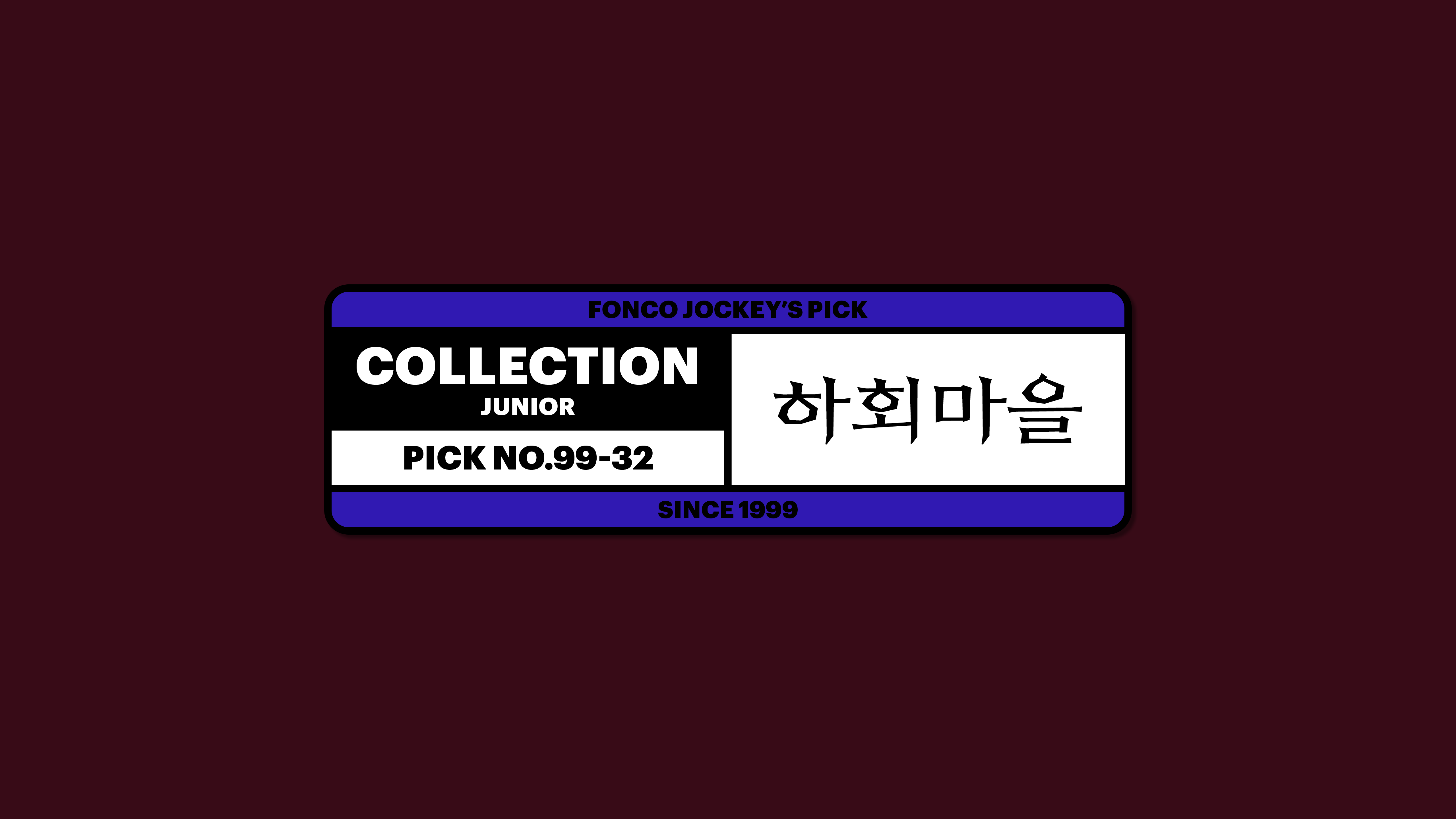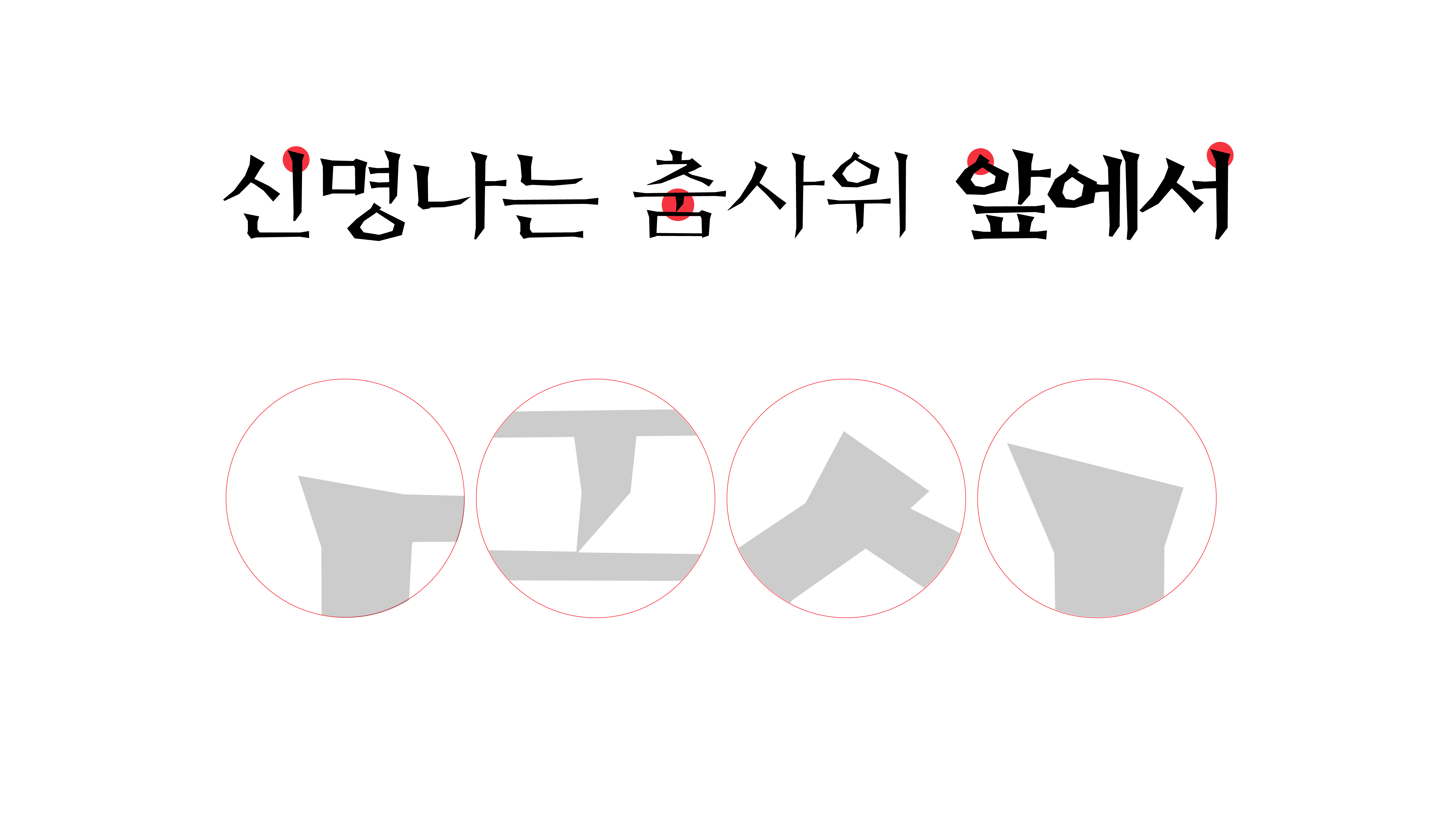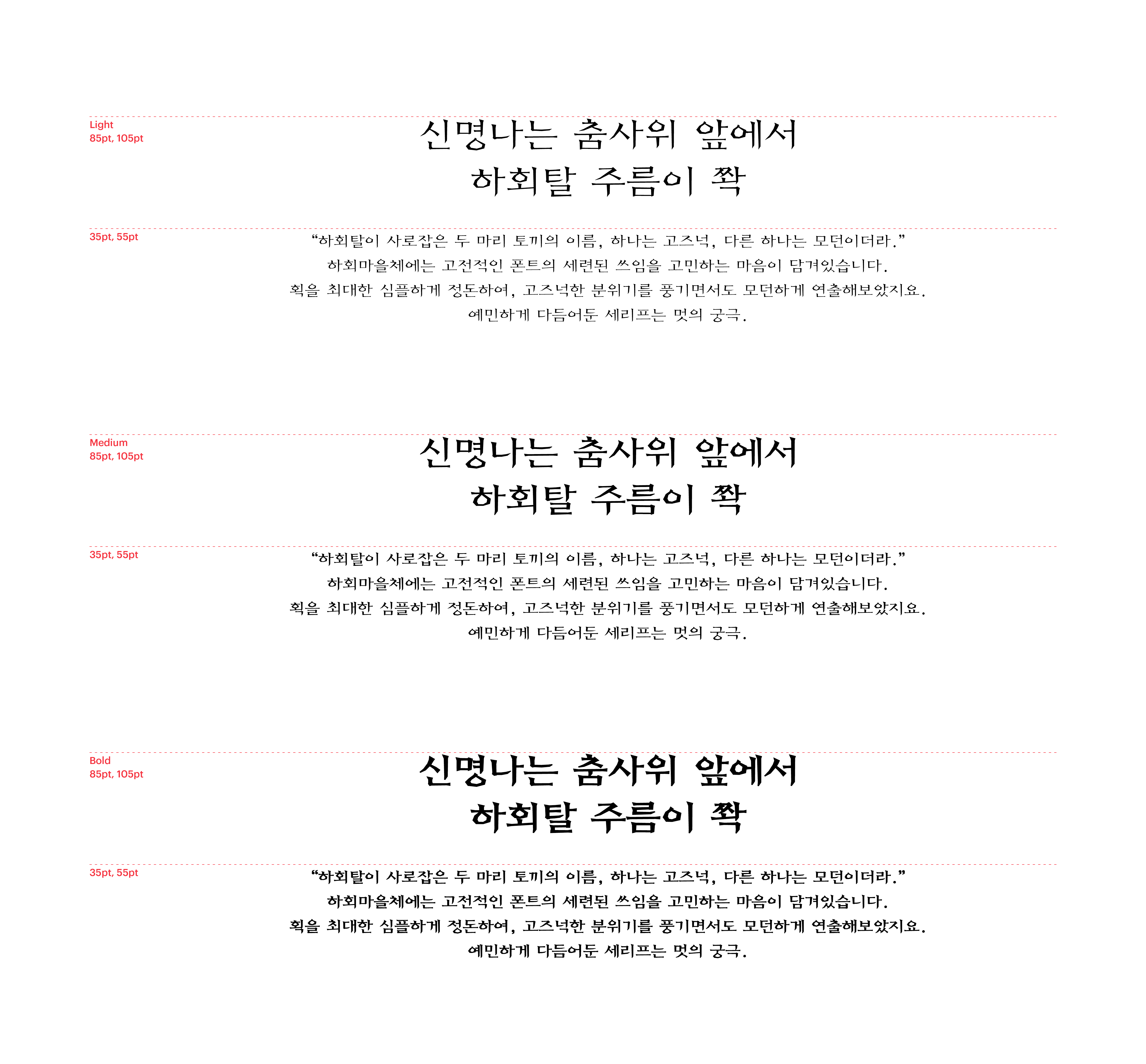
하회마을
Yoon 하회마을
하회마을체에는 고전적인 폰트의 세련된 쓰임을 고민하는 마음이 담겨있습니다. 획을 최대한 심플하게 정돈하여, 고즈넉한 분위기를 풍기면서도 모던하게 연출해보았지요. 예민하게 다듬어 둔 세리프는 멋의 궁극. 현대적 긴장감과 고전미를 동시에 선사하는 하회마을체를 통해 색다른 아름다움을 체험해보세요.